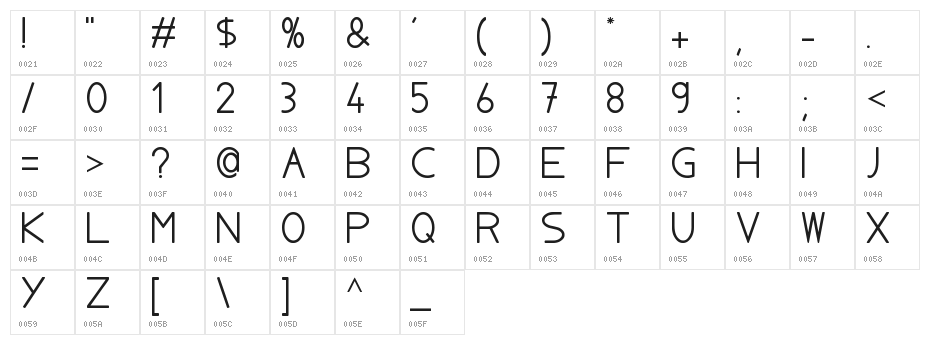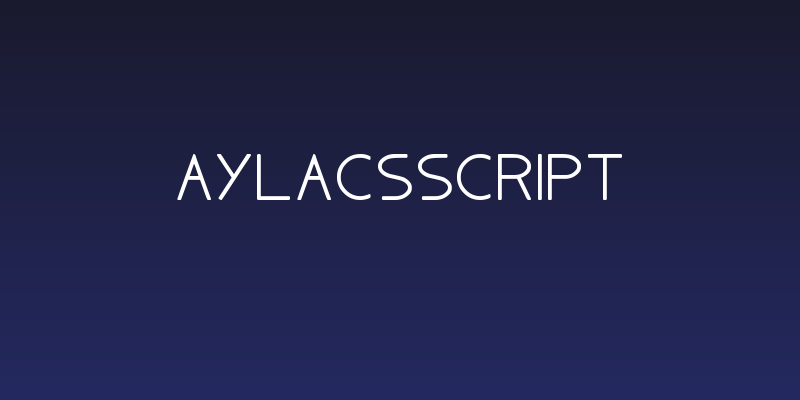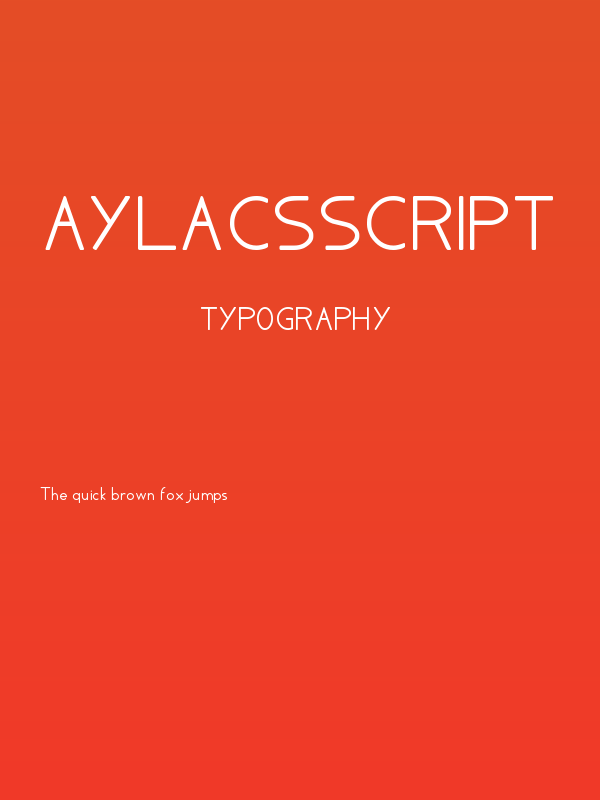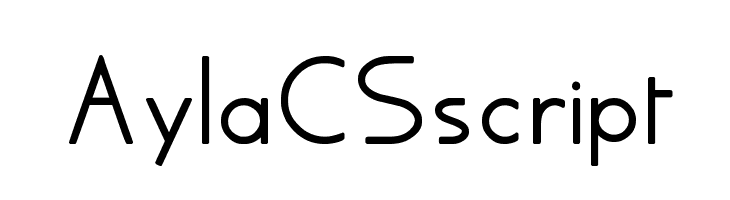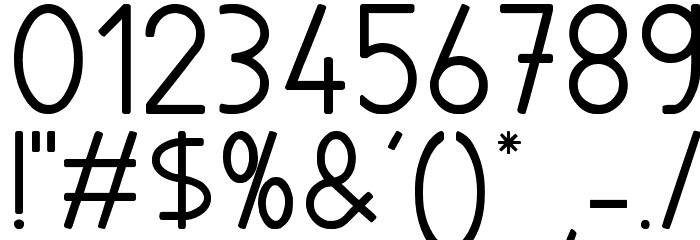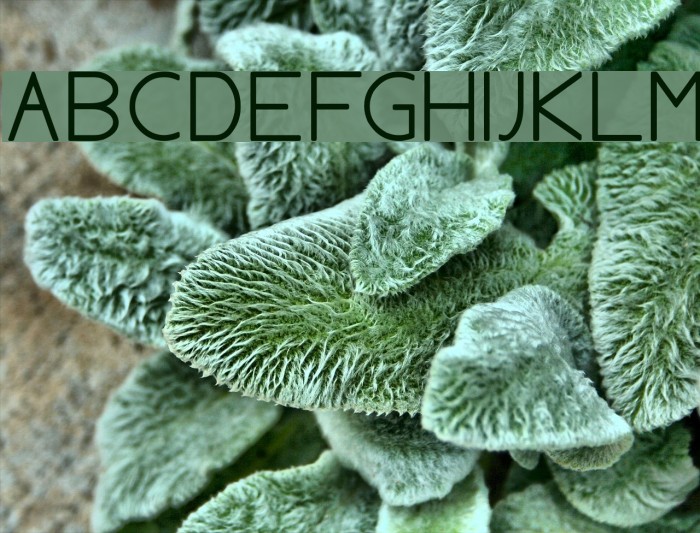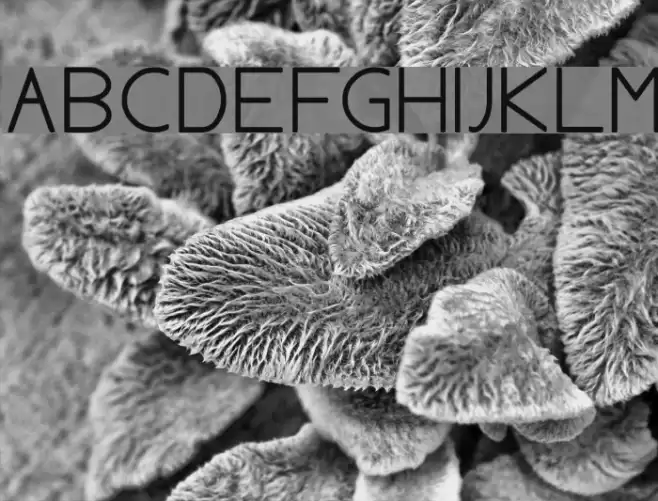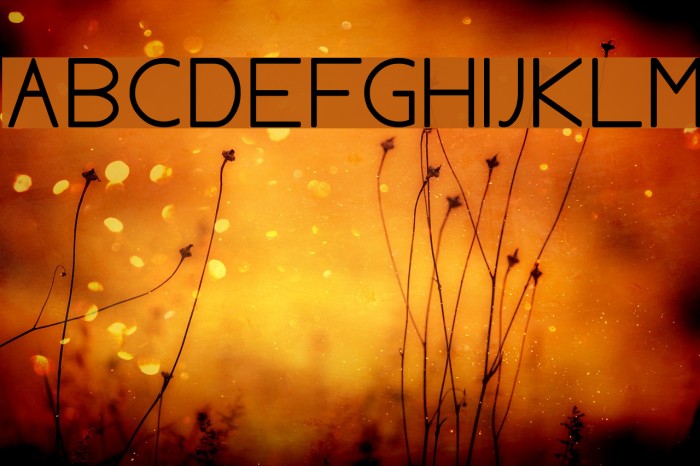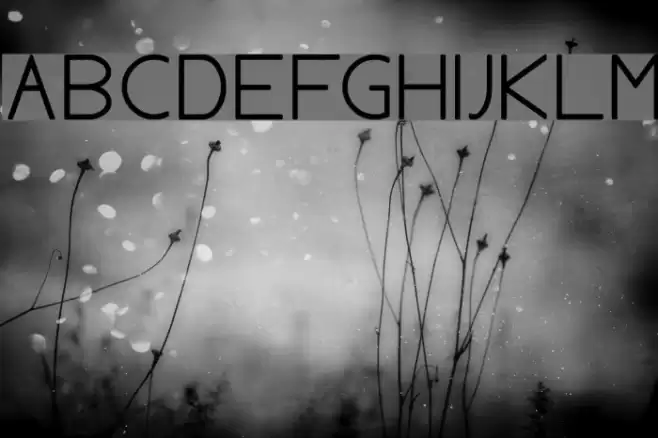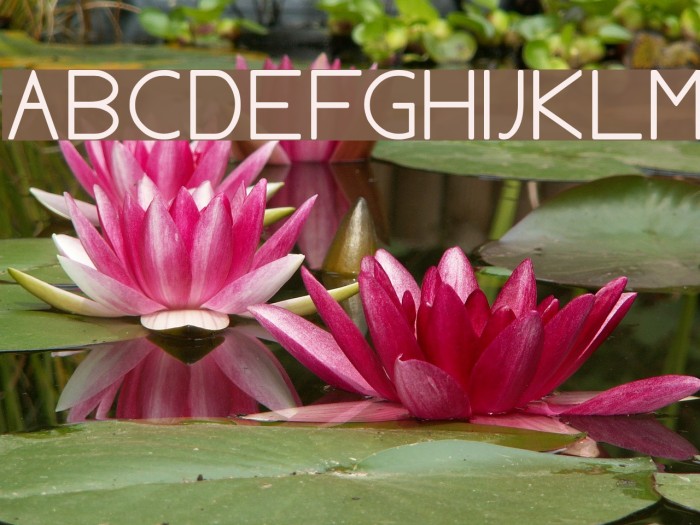
AylaCSscript Font
✎ Sans Serif
| الفئات | Sans Serif |
| حالة الاستخدام | Headlines, Body text, Logos |
| مشاريع مقترحة | Ideal for branding, web design, advertising, and editorial layouts where clarity and modernity are key. |